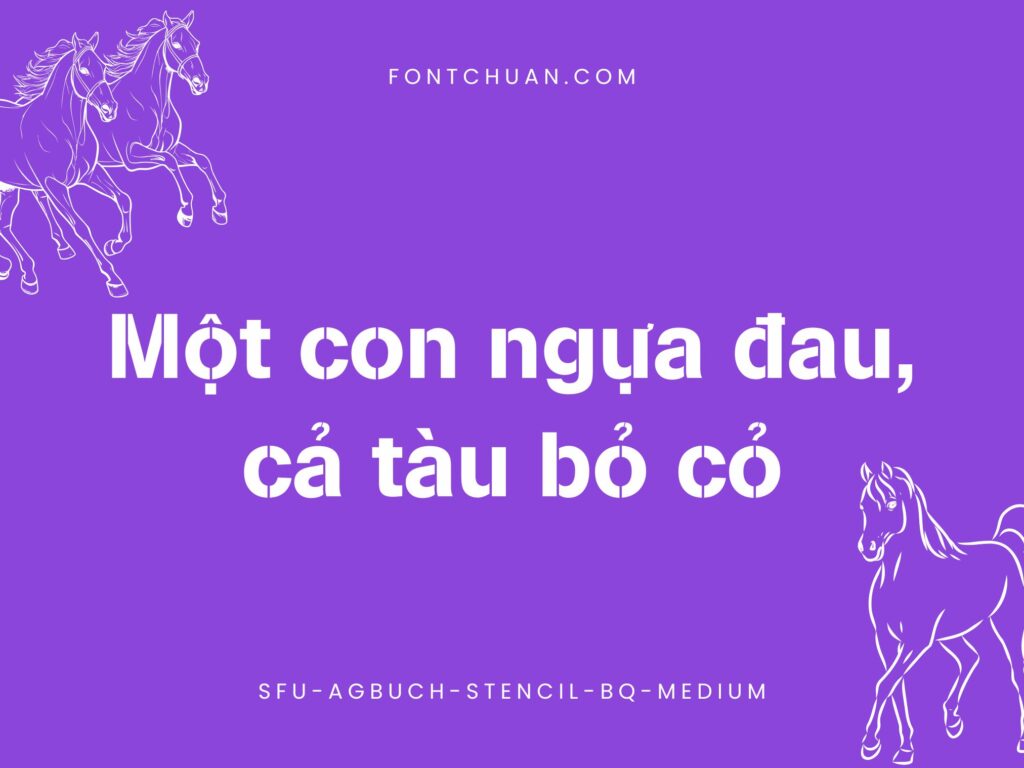
Font SFU Agbuchstencilbq Việt Hóa
Font SFU AGBuchStencilBQ Medium là một kiểu chữ stencil độc đáo, mang phong cách công nghiệp và hiện đại. Với các đường nét mạnh mẽ và thiết kế dạng stencil, font này tạo cảm giác chắc chắn và chuyên nghiệp. Đây là lựa chọn lý tưởng cho các thiết kế cần sự nổi bật và cá tính.
SFU AGBuchStencilBQ Medium phù hợp cho các dự án thiết kế logo, tiêu đề, bao bì sản phẩm và các ấn phẩm quảng cáo. Các ngành nghề như quảng cáo, giáo dục và công nghệ có thể tận dụng font này để tạo điểm nhấn trong thiết kế. Ngoài ra, font cũng thích hợp cho các sự kiện như Tết, Giáng sinh, Valentine và các lễ hội khác.